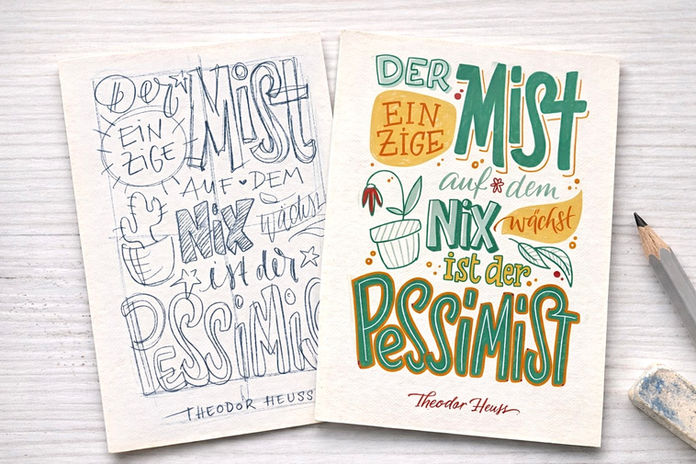
Sushimoons Lettering-Backstube - Buchstaben zeichnen locker und leicht
Passend zum Sonntagnachmittagskaffee zeige ich dir in diesem Kurs mein persönliches Rezept mit Geling-Garantie:
Wie du mit tollen Buchstabenvarianten wahre Eyecatcher-Postkarten gestaltest, die nicht nur hübsch aussehen, sondern richtig Eindruck machen.
Wir stecken die Hände tief in den Teig des Buchstabenzeichnens und du lernst Schritt für Schritt, wie aus einzelnen Formen, Kontrasten und Stilvarianten eine starke Komposition entsteht. Wir gestalten wunderschöne Schriften und backen daraus ein richtig schmackhaftes Lettering.
• spannende Buchstabenvarianten
• Stil-Experimente
• Schrift in Formen
• Tricks & Hacks für Layout und Komposition
• Sushimoons volle Buchstabenliebe
Nach diesem Kurs kennst du ein wunderbares Lettering-Rezept und hast viel Neues über Schrift kennengelernt, damit kannst du dann:
• Buchstaben bewusst zeichnen statt nur schreiben
• deinen Letterings Mehr Details und Highlights schenken
• deine individuellen Glückwunschkarten, Poster oder Banner selbst gestalten
Mit meiner klaren Zutatenliste führe ich dich sicher durch die Welt der Buchstaben. Und für alle, die etwas mehr Streusel wünschen, habe ich eine Menge Raffinessen in meiner Trickkiste, sodass jede Karte auch ihr Sahnehäubchen bekommt.